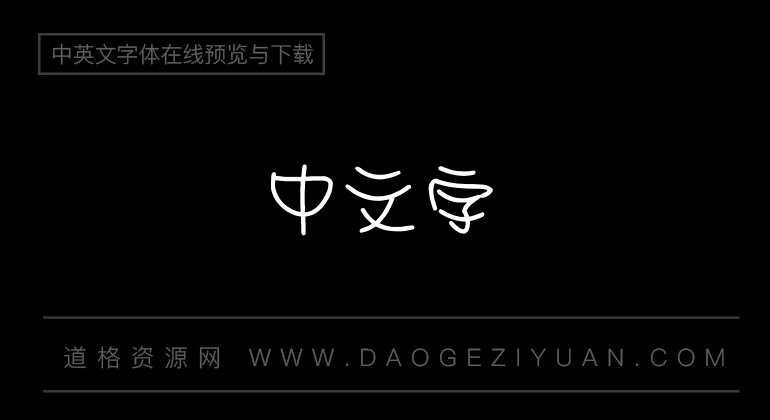
金梅浪漫中圆字体是一款精致的中文字体,由金梅浪漫设计团队设计。该字体以中国传统文化为灵感,融合了各种中国传统文化元素,如仪式感、节日感、艺术感等,让字体更加浪漫而又精致。其字形细腻,笔画流畅,线条细腻,让字体充满时尚感。它可以用于文字设计,也可以用于平面设计,让设计更加生动、有趣。文件名:JinMeiLangManZhongYuanZiTi-1.ttf
金梅浪漫中圆字体是一款非常不错的手写艺术字体,具有很好的视觉感,适合于文化类的宣传设计、商业类品牌的广告和产品包装设计以及个性化文字排版等较多场景。